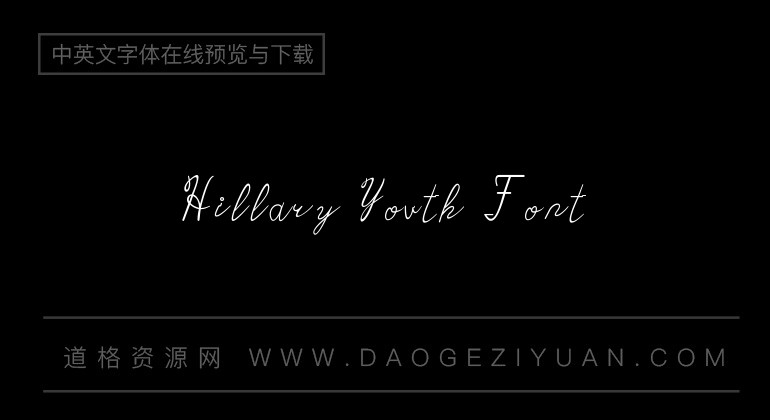
Hillary Youth Font
Hillary Youth Font 是一款基于手写风格设计的字体。它的设计风格非常活泼、自然,适合用于年轻,时尚的设计项目。这款字体的笔画非常流畅,有一种轻快的感觉,与众不同的线条设计使得它更加醒目。Hillary Youth Font 字体支持多种语言文字,包括英文、中文、日文、韩文等,因此可以满足多种设计需求。Hillary Youth Font 字体的下载和使用也非常方便,可以应用于海报设计、书籍排版、名片设计等多个方面。
Hillary Youth Font是一款非常不错的手写艺术字体,具有很好的视觉感,适合于文化类的宣传设计、商业类品牌的广告和产品包装设计以及个性化文字排版等较多场景。